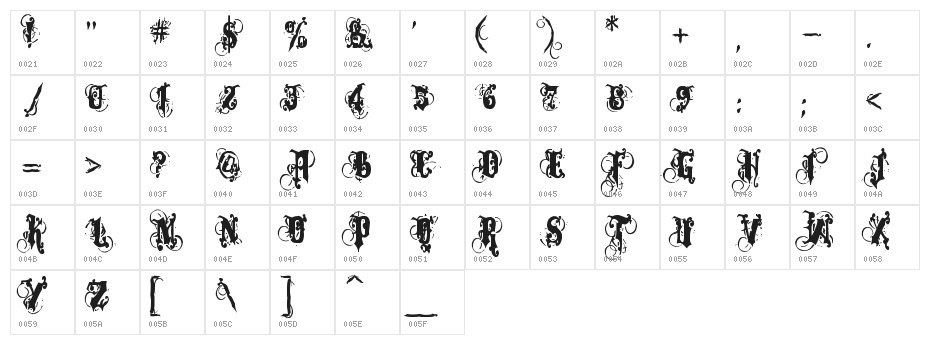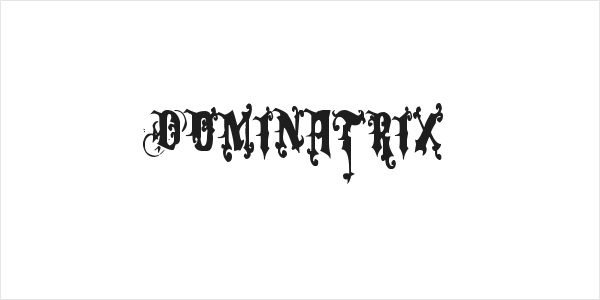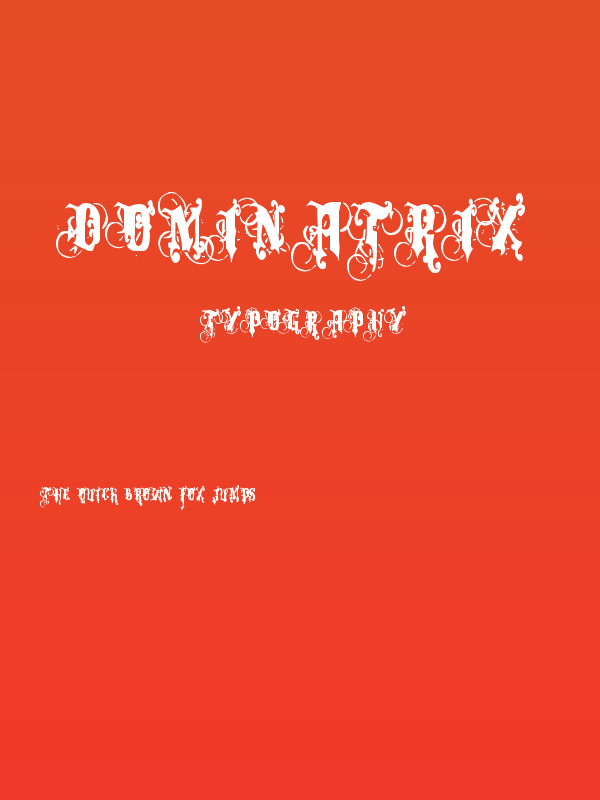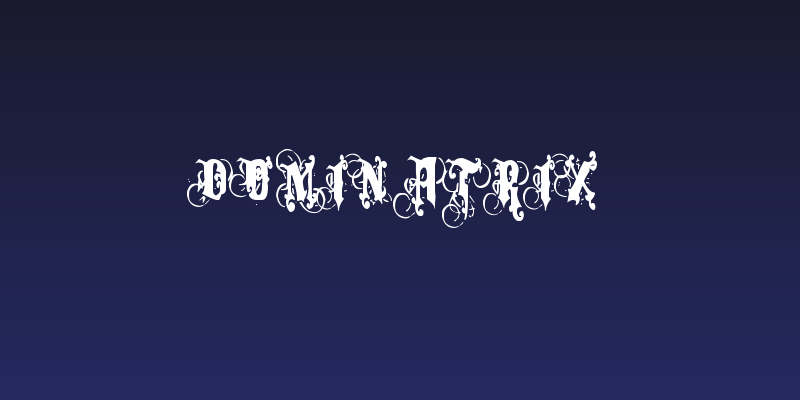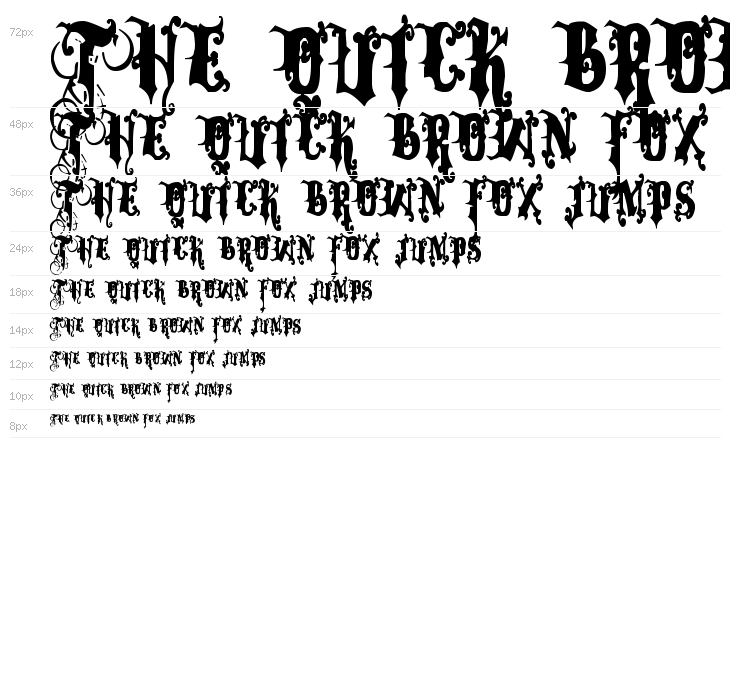
Dominatrix Font
✎ Gothic
| श्रेणियाँ | Gothic |
| कंट्रास्ट | High |
| समग्र शैली | Gothic, Decorative |
| उपयोग का मामला | Logos, Headlines, Posters |
| सुझाए गए प्रोजेक्ट | Ideal for tattoo designs, gothic-themed posters, album covers, and decorative invitations. |